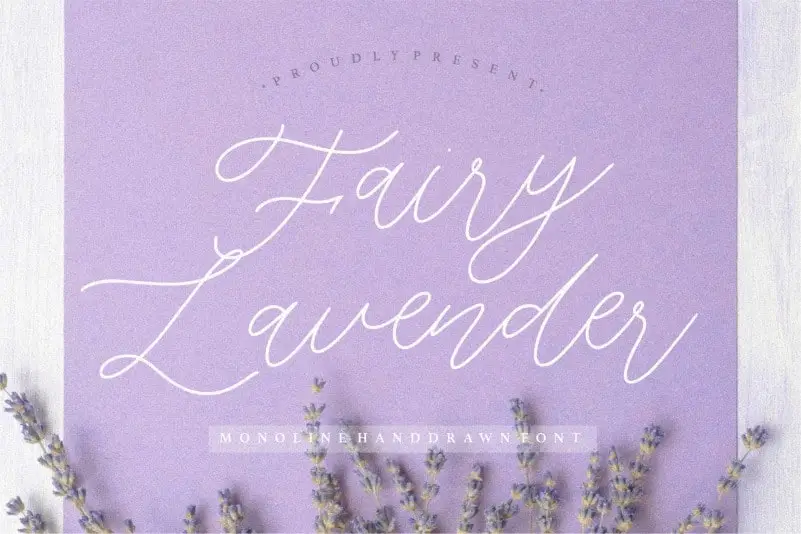
Fairy Lavender Monoline Handdraw Font – Fonte Grátis
Fairy Lavender Monoline Handdraw Font
A Fairy Lavender Monoline Handdraw Font é uma opção ideal para quem busca estilos criativos e diferentes para seus projetos digitais. Com um tom suave e aconchegante, essa fonte hand-drawn é perfeita para aplicar em diversos ambientes, desde embalagens de produtos até design editorial. Seu nome sugere uma atmosfera delicada e encantadora, lembrando da frescura das hortências lavanda que envolvem a natureza com seu perfume suave. Para o designer balpirick, essa fonte é mais do que um recurso gráfico, ela transmite um amor pela arte hand-drawn. Suas linhas delicadas e curvas perfeitas criam uma experiência visual única que se destaca em qualquer meio de comunicação digital. Seja para criar embalagens memoráveis ou personalizar o texto de sites de redes sociais, Fairy Lavender é uma escolha inteligente para quem busca algo especial e único. Agora mais do que nunca, a personalização e o estilo diferenciado são essenciais nas mídias digitais. Com a Fairy Lavender Monoline Handdraw Font, você pode adicionar um toque de elegância ao seu trabalho, seja ele uma embalagem sofisticada ou conteúdo digital criativo para redes sociais. Seja qual for sua necessidade em design editorial, essa fonte é certamente uma opção que merece ser considerada.